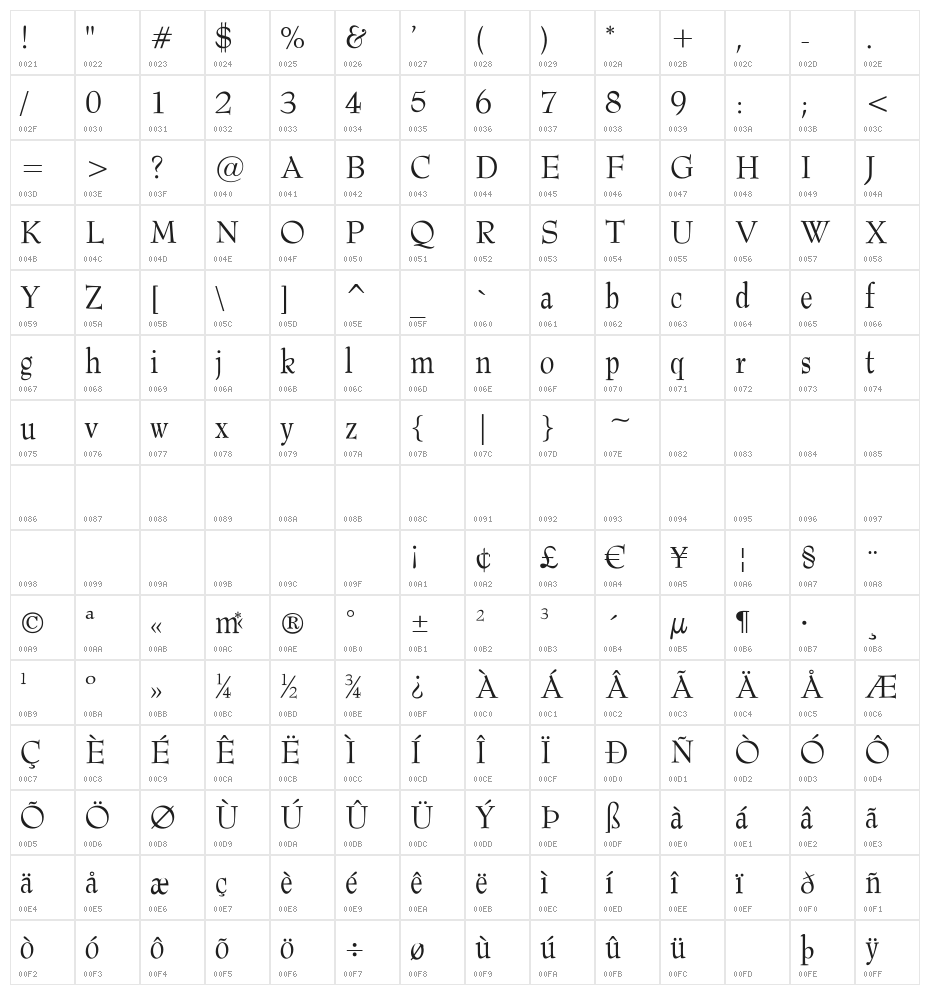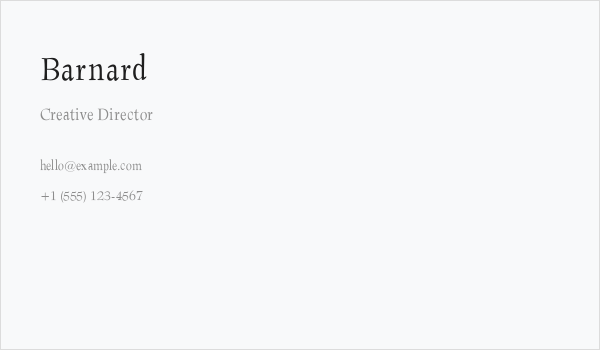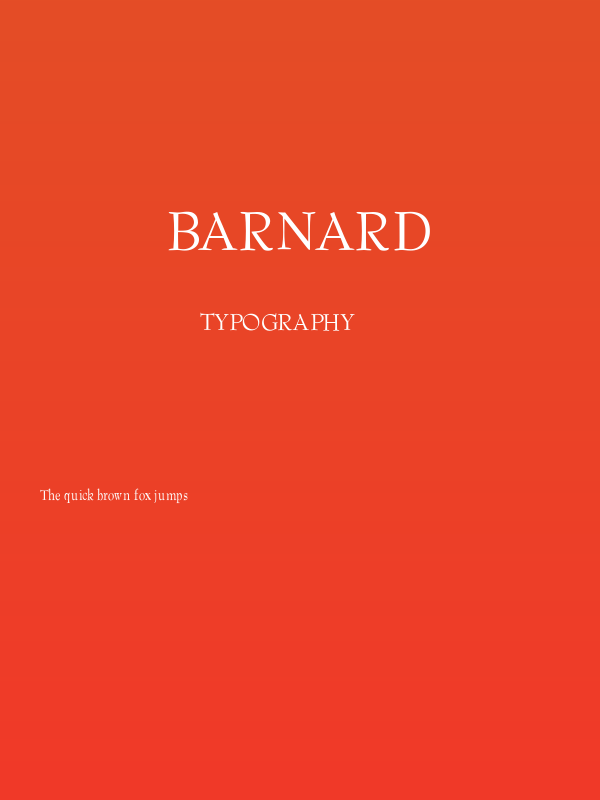
Barnard Font
| النمط العام | Classic |
| حالة الاستخدام | Headlines, Body text, Logos |
| مشاريع مقترحة | This font is perfect for projects that require a touch of elegance and tradition, such as book covers, formal invitations, editorial layouts, and branding for luxury products. |